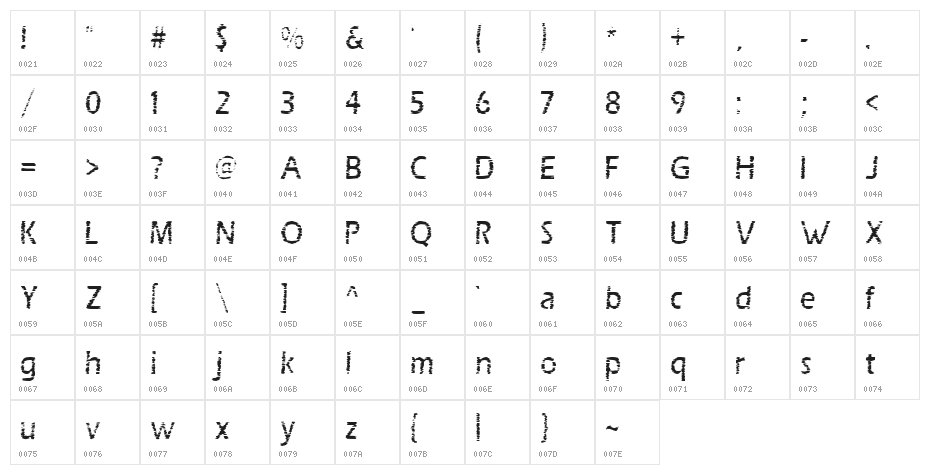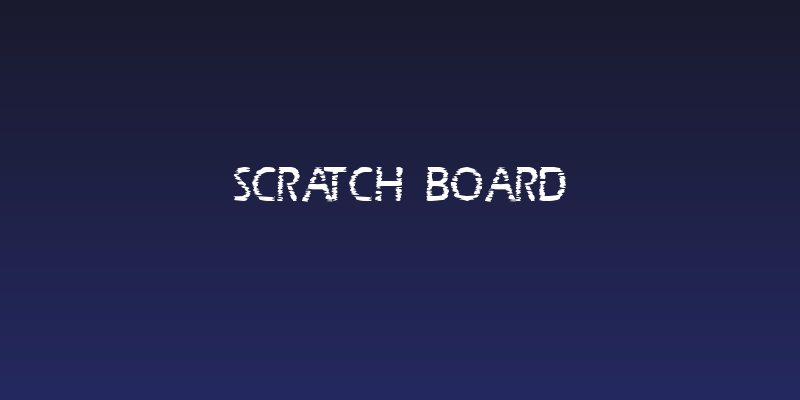
Scratch Board Font
| Progetti proposti | Ideal for posters, album covers, branding for alternative events, or any project needing a gritty, urban aesthetic. |